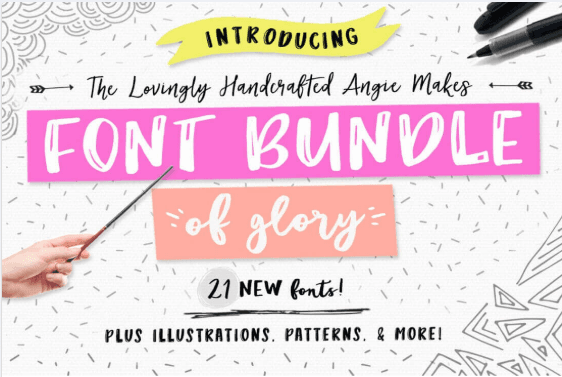
Glorious Font Bundle: 21 Fonts, 60 Patterns, 200 Doodles
«Удивительный ручной шрифт» от Angie Makes - это настоящая вечеринка. Вы возьмете домой 21 восхитительный шрифт ручной работы, охватывающий все - от рукописных сценариев до всех засечек. Но вы также получите 60 образцов Photoshop, 200 восхитительных рисунков и 21 шаблон логотипа, чтобы объединить все это в один великолепный шедевр.
Особенности:
21 уникальных, нарисованных от руки шрифтов. Международная языковая поддержка.
60 узоров Photoshop - черно-белые, разноцветные геометрические, блестящие золотые текстуры и т. Д.
200+ каракулей - милые животные, водовороты, перепады, сердечки, цветы, стрелы.
21 Шаблоны логотипов - руководство по сопряжению шрифтов предлагает помощь в создании бесчисленных логотипов.
Идеальная коллекция для создания этикеток, наклеек, логотипов, брендинга, упаковки, одежды, обложек книг, сумок, открыток, приглашений и многого другого.